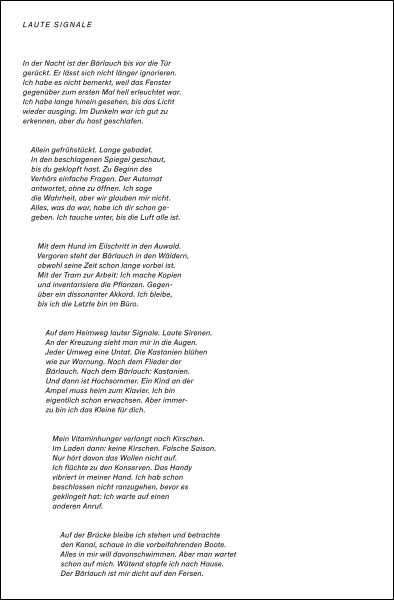
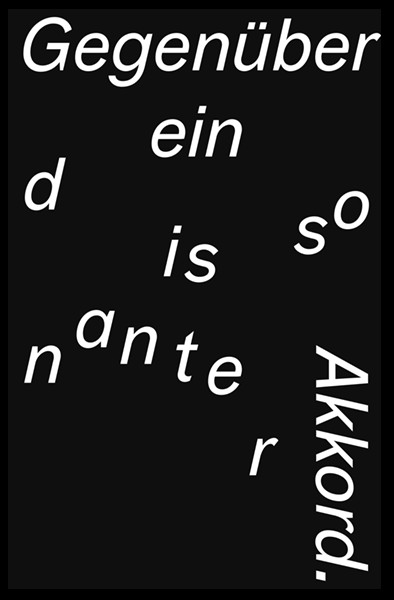
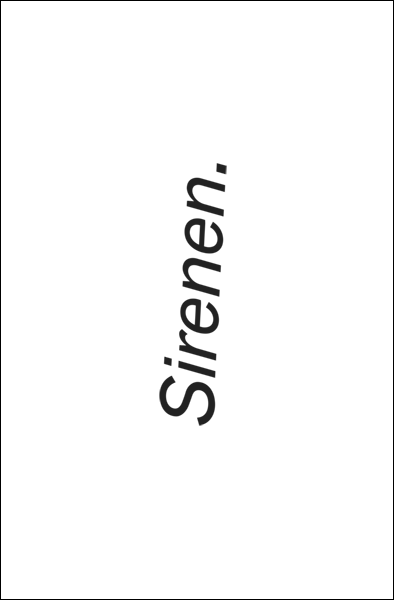
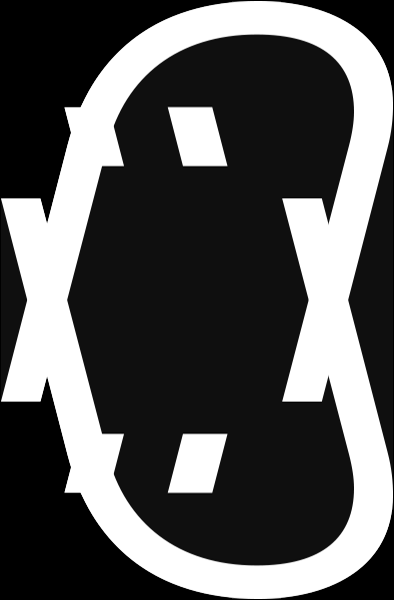
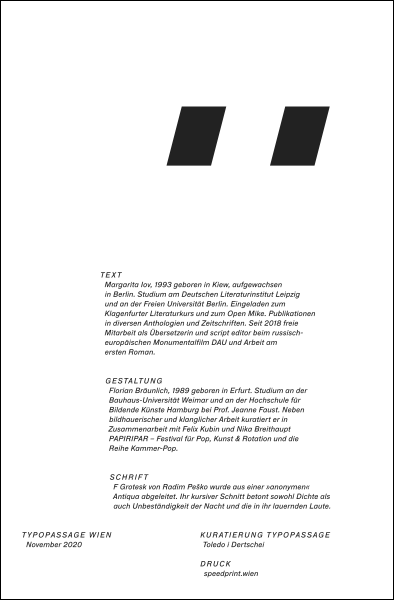
Text
Margarita lov, 1993 geboren in Kiew, aufgewachsen in Berlin. Studium am Deutschen Literaturinstitut Leipzig und an der Freien Universität Berlin. Eingeladen zum Klagenfurter Literaturkurs und zum Open Mike. Publikationen in diversen Anthologien und Zeitschriften. Seit 2018 freie Mitarbeit als Übersetzerin und script editor beim russisch-europäischen Monumentalfilm DAU und Arbeit am ersten Roman.
Typografie
F Grotesk von Radim Peško wurde aus einer „anonymen” Antiqua abgeleitet. Ihr kursiver Schnitt betont sowohl Dichte als auch Unbeständigkeit der Nacht und die in ihr lauernden Laute.
Gestaltung
Florian Bräunlich, 1989 geboren in Erfurt. Studium an der Bauhaus-Universität Weimar und an der Hochschule für Bildende Künste Hamburg bei Prof. Jeanne Faust. Neben bildhauerischer und klanglicher Arbeit kuratiert er in Zusammenarbeit mit Felix Kubin und Nika Breithaupt Papiripar – Festival für Pop, Kunst & Rotation und die Reihe Kammer-Pop.